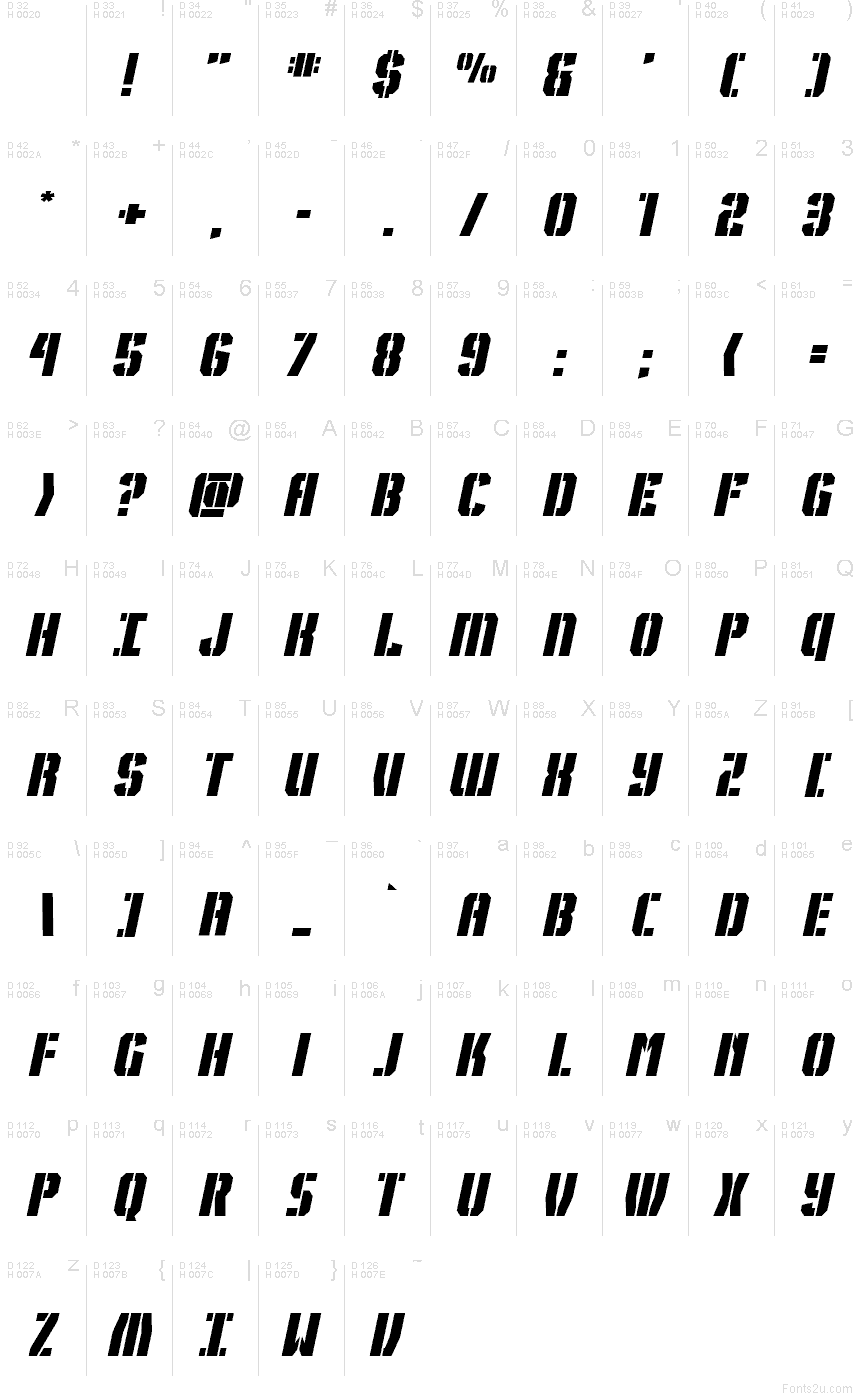
Gorilla Warfare Wide Italic von Iconian Fonts ist eine kostenlose, militärisch anmutende Display-Schrift mit dynamischen, nach vorne geneigten Großbuchstaben. Die Buchstaben wirken wie aus Panzerplatten geschnitten: Scharfe Winkel, tiefe Schnitte und schmale Zwischenräume verleihen dieser Schrift einen rauen, taktischen Rhythmus, statt eines sanften, sportlichen Neigungswinkels.
Die Schrift ist ideal für Plakatüberschriften, Gaming-Branding, Filmtitel, E-Sports-Grafiken und markante Schlagzeilen, bei denen ein kostenloser Font Kraft zeigen soll, ohne generisch zu wirken. Perfekt für kurze Texte, Logos oder Monogramme, da die aggressiven Schnitte und die komprimierte Energie ihre volle Wirkung entfalten, wenn die Buchstaben Platz zum ‚Zuschlagen‘ haben.